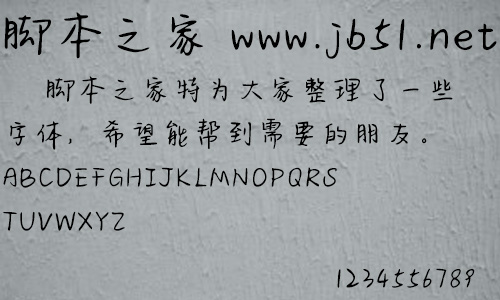
字心坊左岸戀人字體是一款有字心坊字庫出品的藝術(shù)字體,該字體字形清秀,筆劃秀美,起轉(zhuǎn)承合縱任奔逸,字形大小不一,正倚交錯,令其整體上極具韻律感。這款字體適合應(yīng)用于藝術(shù)設(shè)計、平面宣傳設(shè)計、網(wǎng)頁設(shè)計,書法字帖等領(lǐng)域,歡迎需要的朋友前來本站下載使用。